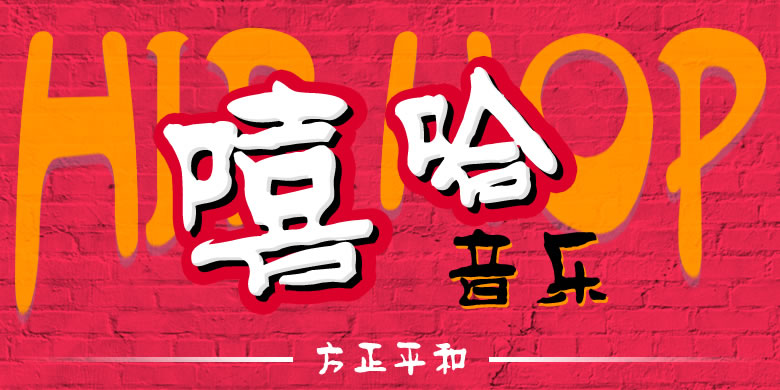
方正平和
品牌:方正字库设计师:贝威扬发行时间:2000字库编码:大陆简体(GB2312-80)、大陆繁体(GB12345-90)、简繁扩展(GBK)、港台地区(BIG-5)分类:创意书写
方正平和
方正平和体因取唐代书法家孙过庭《书谱》中所倡“志气平和,不激不厉”之意而得名。这款字体的中宫宽松,笔画敦厚,并向下侧挤压,在跌宕起伏的运笔中寻求整体的平稳。方正平和体的风格夸张、放浪不羁、富有拙趣,适用于餐饮、食品、酒类品牌的广告和产品包装设计,以及影视、动漫和游戏的标题用字。